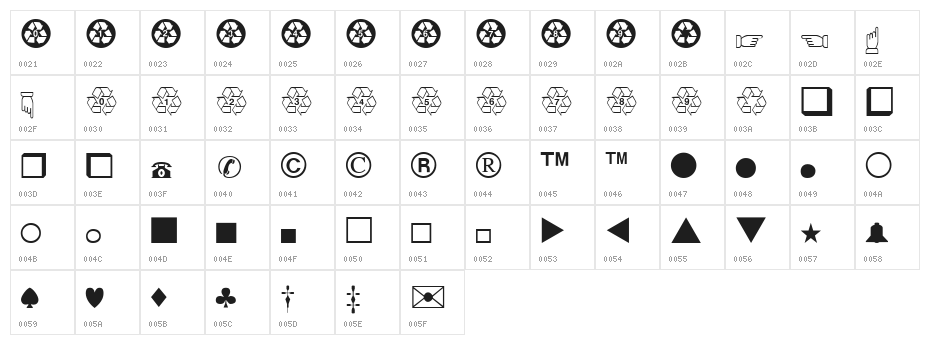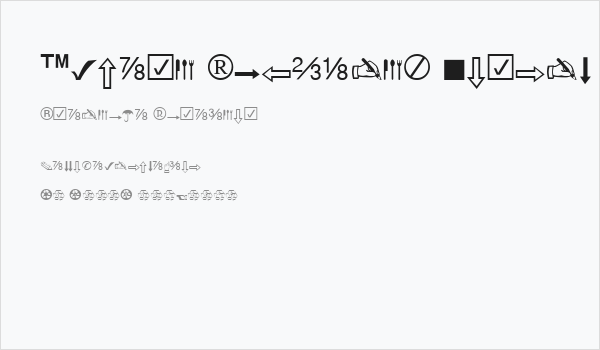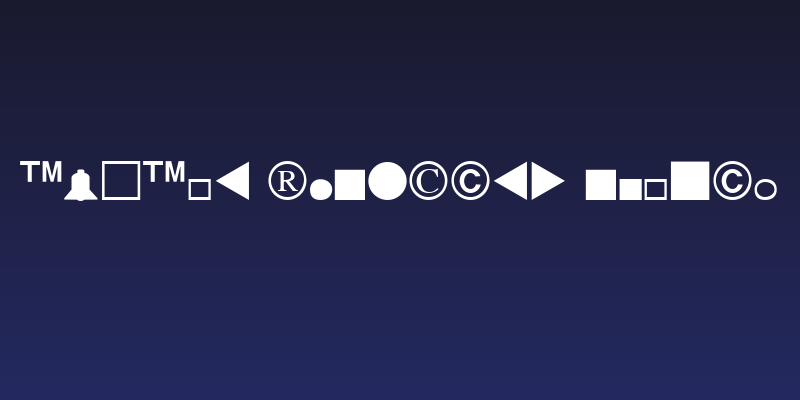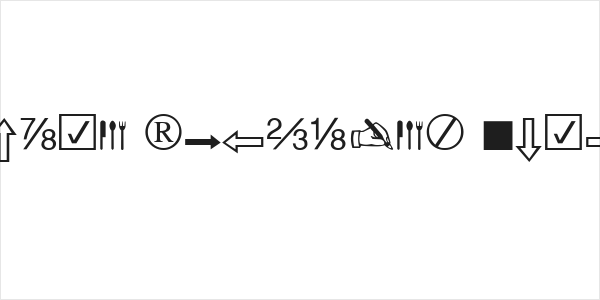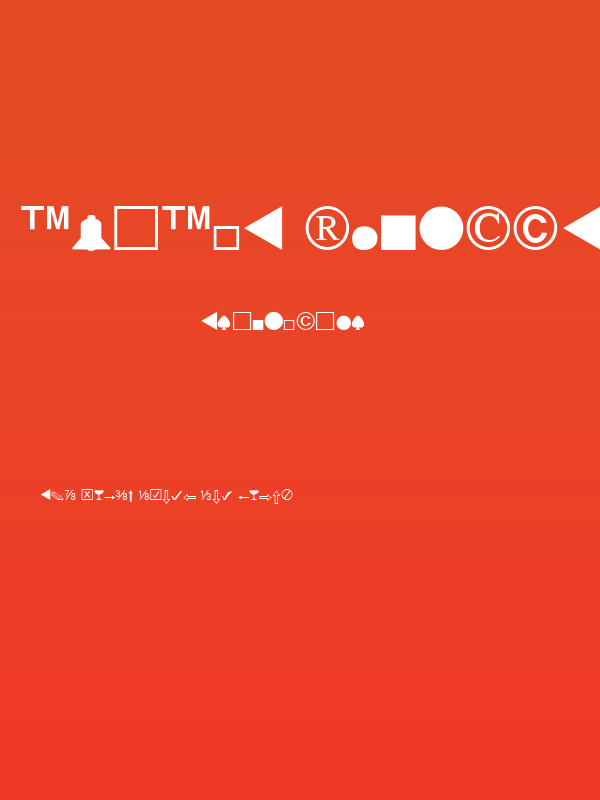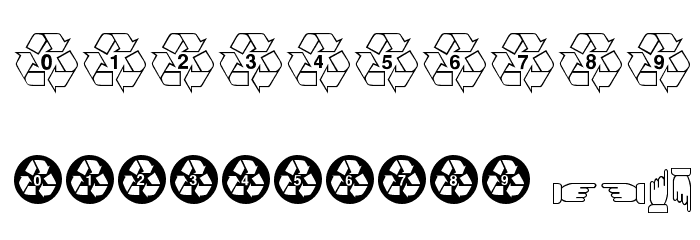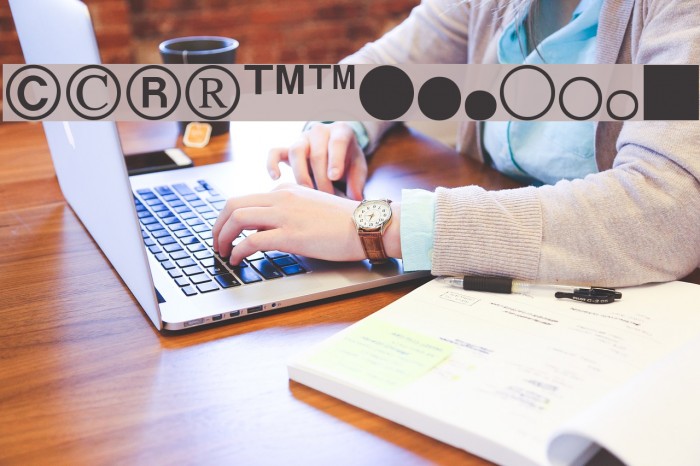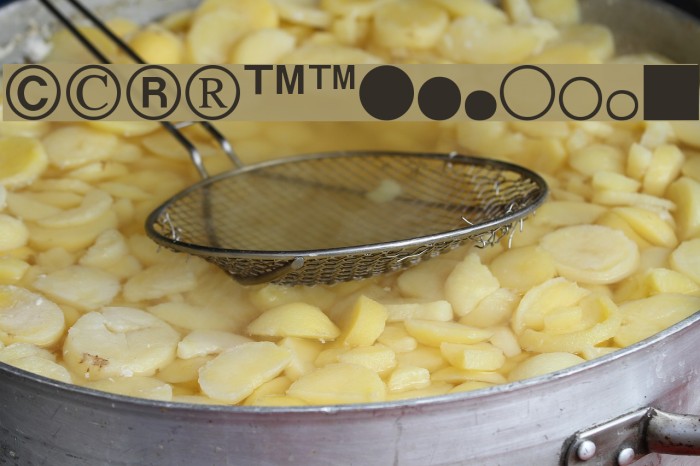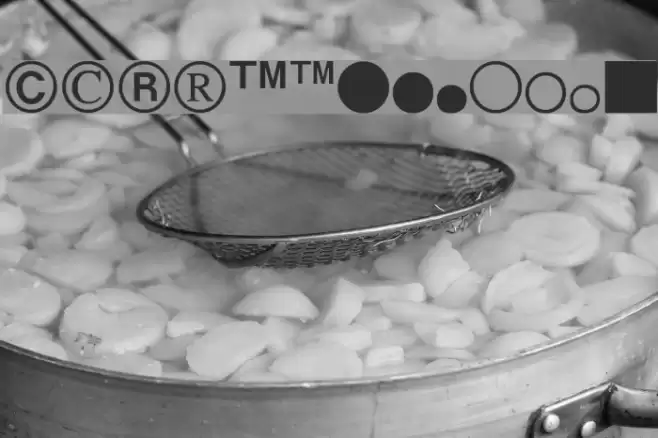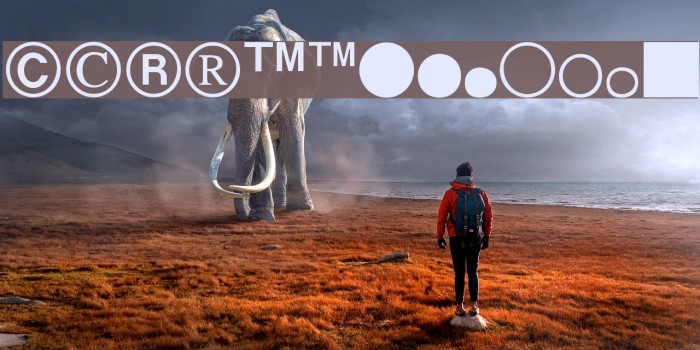
Expert Dingbats Normal Font
| Cas d'utilisation | Icons, Signage, User Interfaces |
| Projets proposés | Ideal for use in instructional materials, signage, user interfaces, and educational resources where clear symbol representation is crucial. |